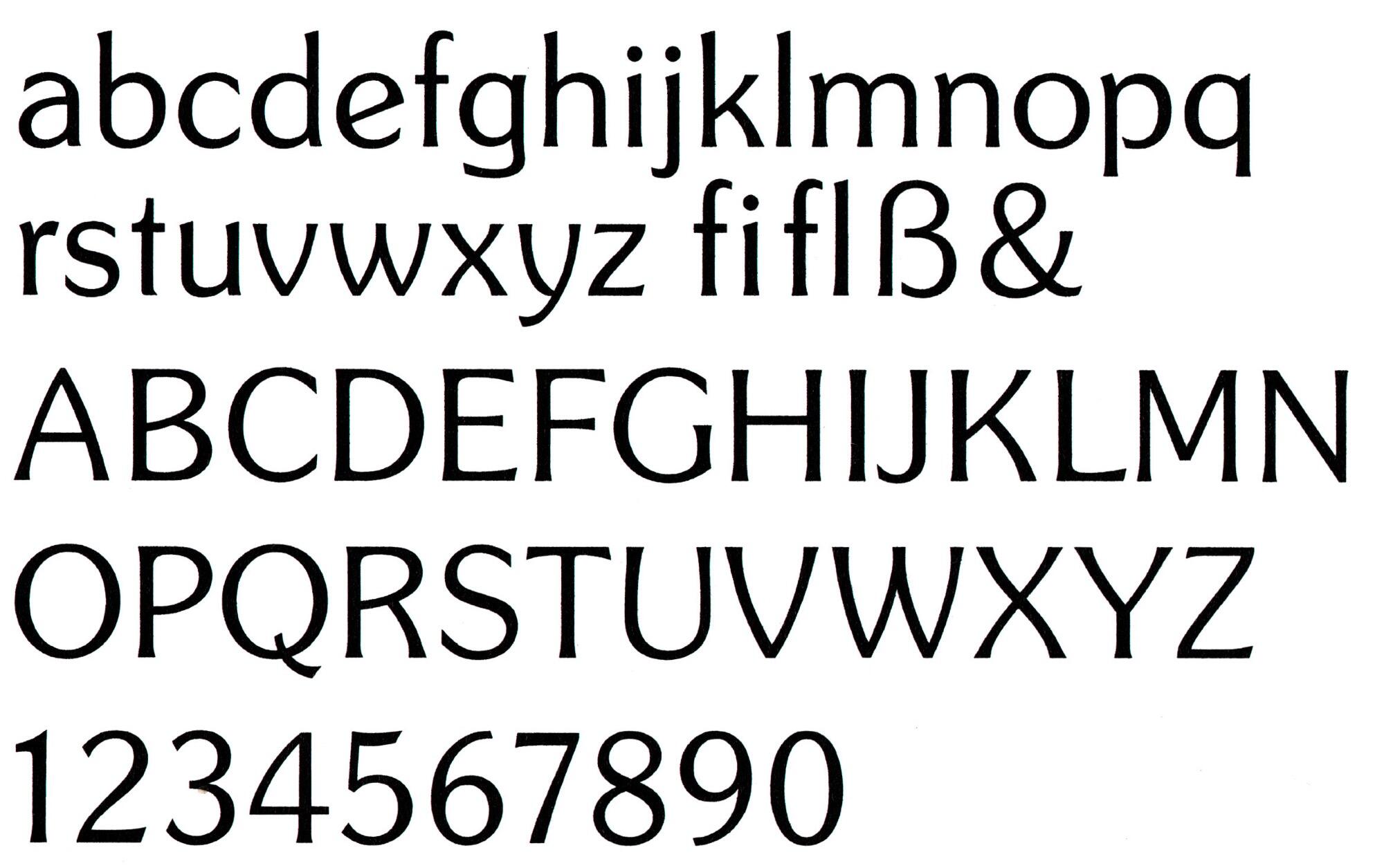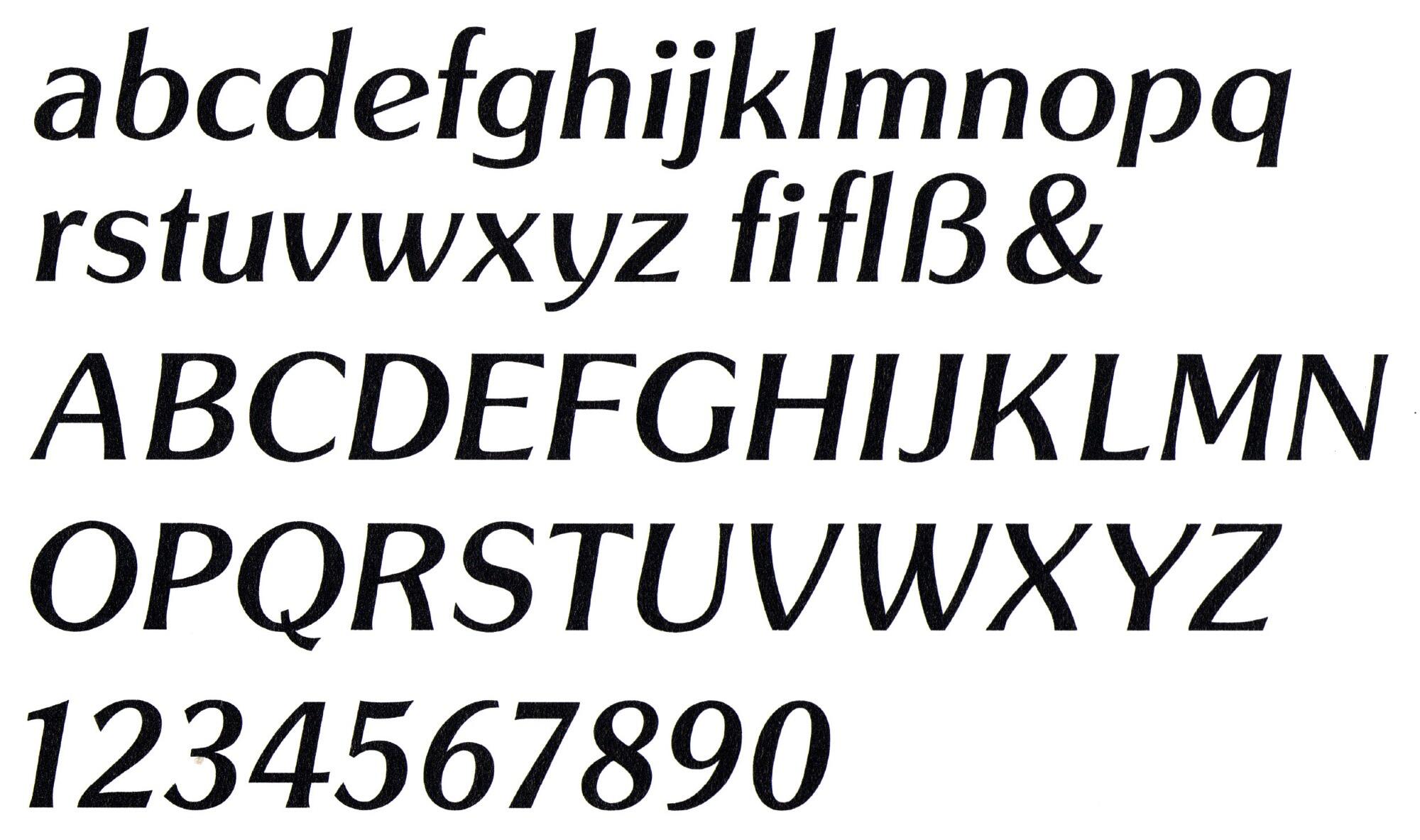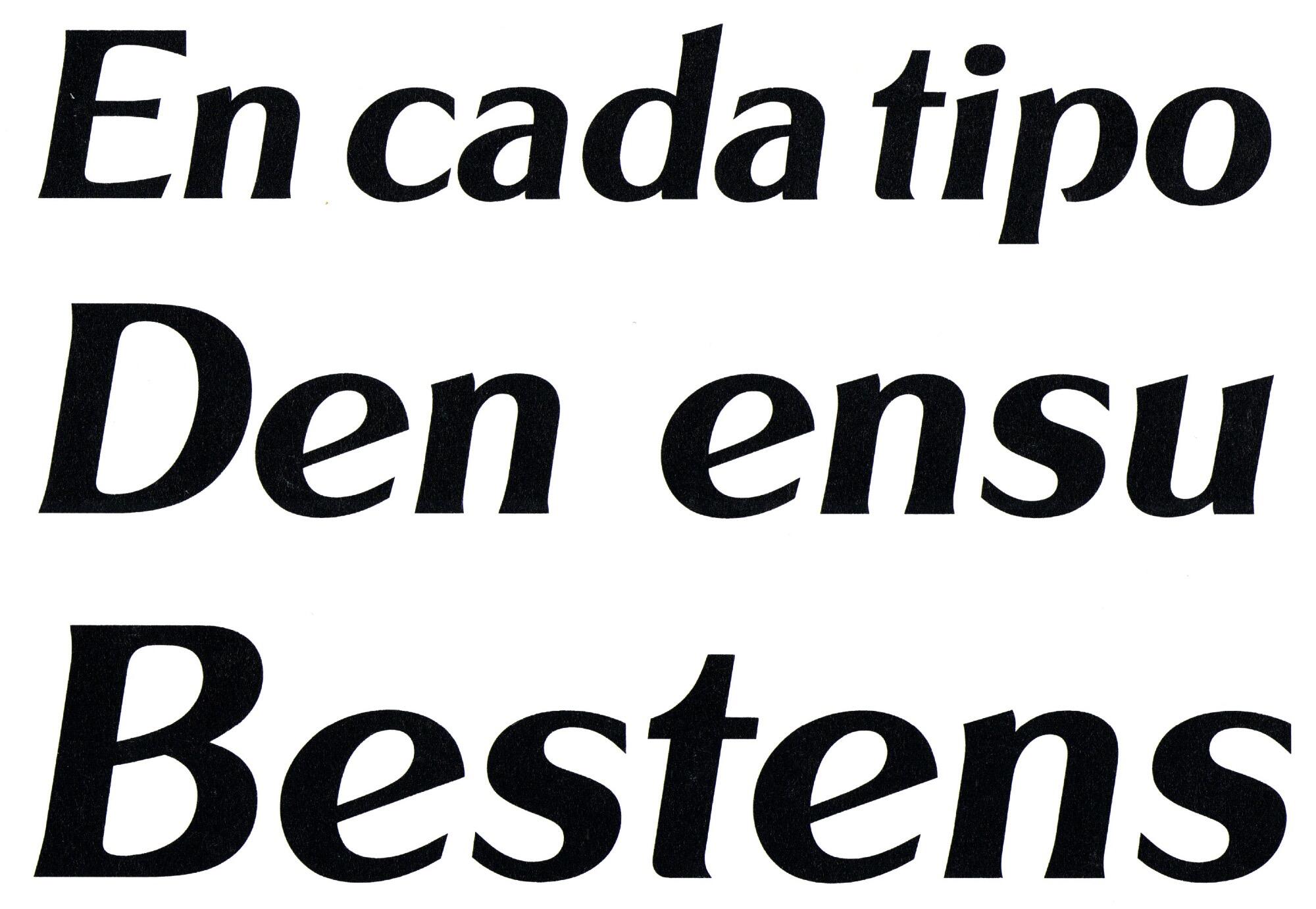
Eine ursprünglich in den 1970er-Jahren für den Fotosatz erschienene Umsetzung der bekannten Souvenir als Groteskversion. Die Schriftfamilie behält die charakteristischen geschwungenen Striche der Souvenir, nimmt die Serifen aber deutlich zurück. Die Schrift erschien in vier Strichstärken, größtenteils mit Kursiven sowie verschiedenen Effektvarianten (u. a. Open, Embossed, Shaded).
Eine digitale Version in sieben Schnitten gibt es von URW.